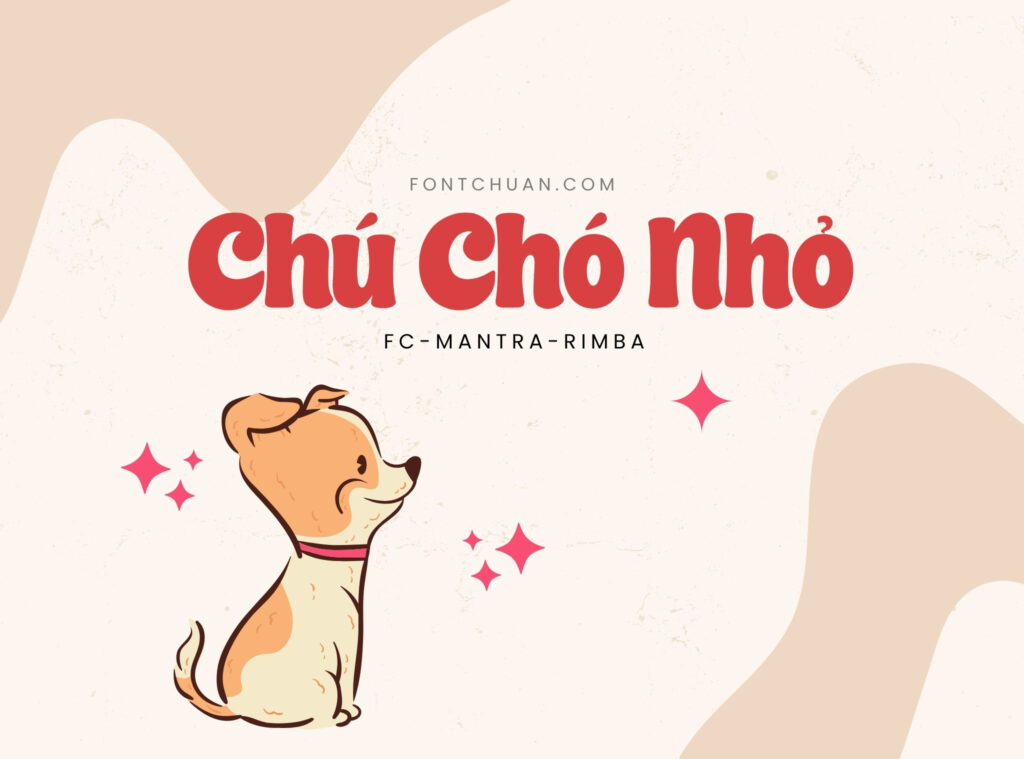
Font Mantra Rimba là một kiểu chữ hiển thị độc đáo, lấy cảm hứng từ vẻ đẹp của thiên nhiên xung quanh chúng ta. Được thiết kế bởi Zain Fahroni và phát hành bởi Four Lines Studio, font này mang đến sự kết hợp giữa sự kỳ diệu của tự nhiên và tính rõ ràng trong thiết kế, giúp truyền tải thông điệp một cách hiệu quả. Nhờ phong cách mềm mại và giàu tính nghệ thuật, Mantra Rimba còn có thể được ứng dụng như một font chữ Trung Thu trong các thiết kế poster, thiệp chúc mừng hoặc banner lễ hội.
Mantra Rimba mặc định hỗ trợ đa ngôn ngữ, bao gồm tiếng Anh, Java, Ý, Cebuano, Malagasy, Swahili, Filipino, Afrikaans, Catalan, Pháp, Đức, Bồ Đào Nha, Thụy Điển và Tây Ban Nha. Phiên bản Font FC Mantra Rimba được Việt hóa miễn phí bởi team Font Chuẩn để hỗ trợ tốt cho tiếng Việt, giúp người dùng Việt Nam dễ dàng áp dụng trong các dự án thiết kế, nhằm đáp ứng nhu cầu đa dạng của cộng đồng thiết kế.
Về đặc điểm thiết kế, FC Mantra Rimba sở hữu phong cách hiển thị với các đường nét tinh tế, tạo nên sự nổi bật và thu hút cho các dự án sáng tạo. Font này phù hợp cho nhiều ứng dụng như logo, đồ họa truyền thông xã hội, Spa làm đẹp, poster và sticker.